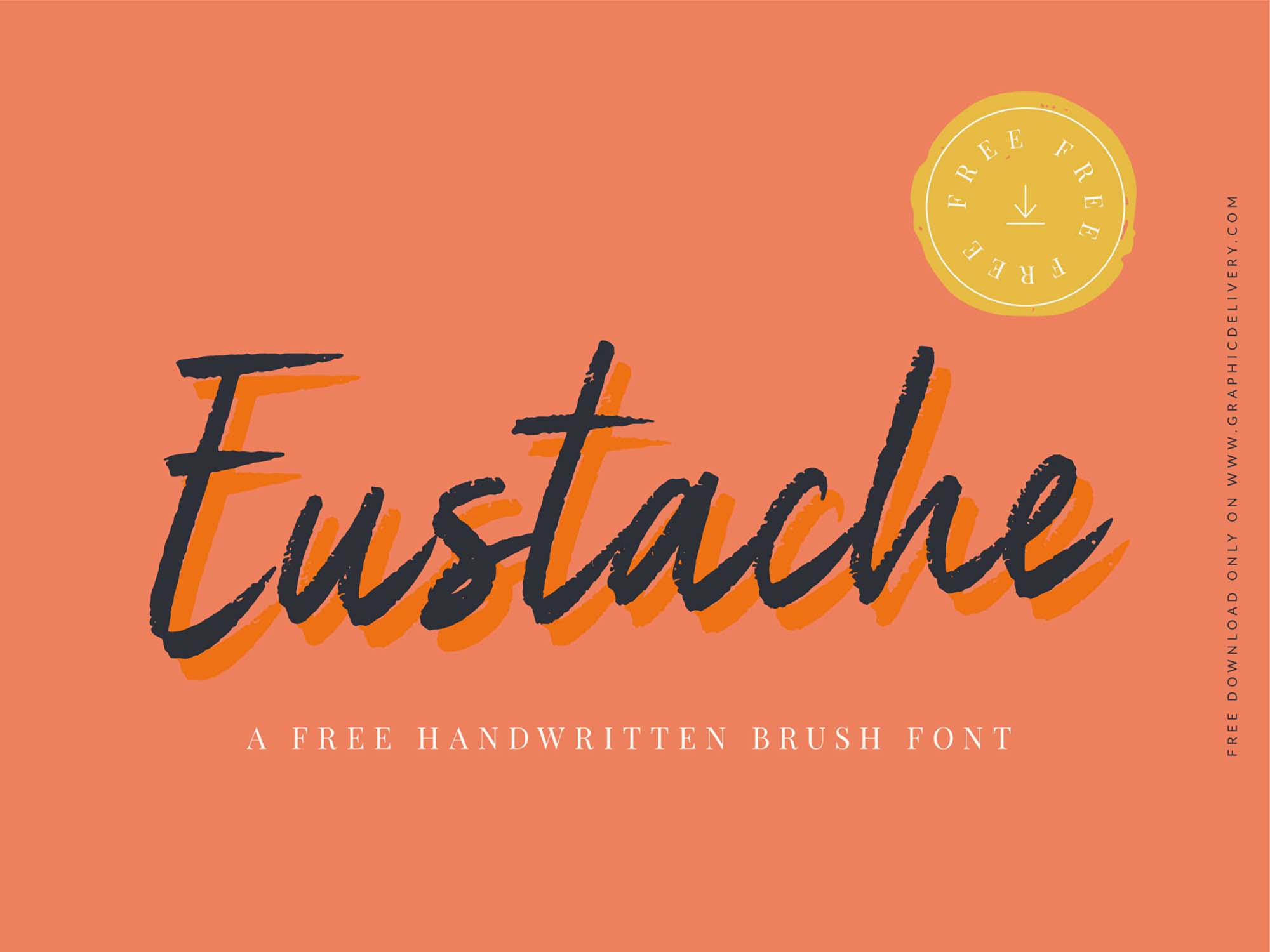
Eustache Brush Handwritten Font – Download Grátis
Eustache Brush Handwritten Font
Descubra o fascínio que a mão escrita desperta nos olhos dos leitores, uma paixão que Eustache Brush Handwritten Font pode despertar. O uso de um efeito de caneta de chumbo em estilo handwritten cria uma conexão imediata, que vai além da aparência do simples texto. Essa fonte é um maravilhoso recurso para capturar e manter a atenção dos espectadores. Seja em uma página de blog, uma página de produto ou uma apresentação, essa fonte irá adicionar um toque único e encantador. Ela não só torna o design mais pessoal, mas também dá o tom certo para qualquer projeto. Eustache Brush Handwritten Font é uma escolha imperdível para quem deseja incorporar um pouco de personalidade e entusiasmo em seus projetos gráficos.